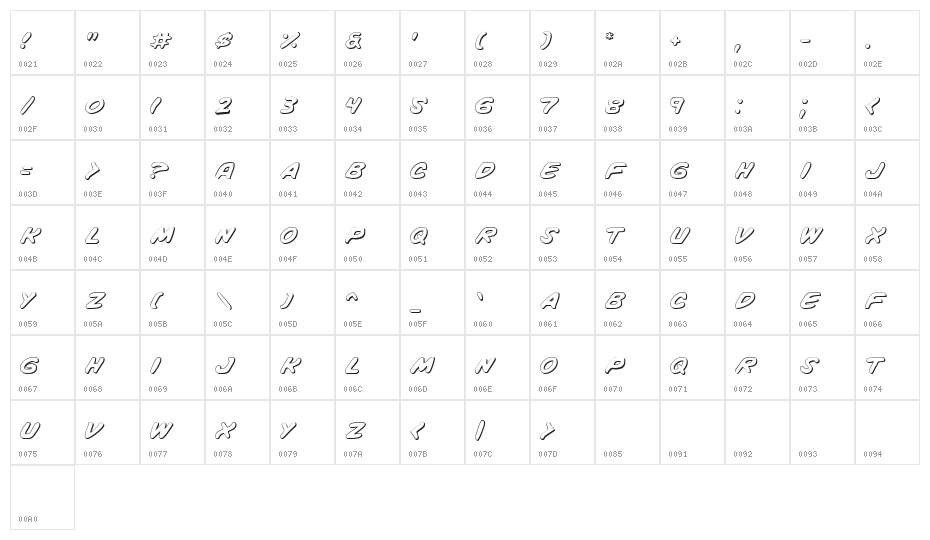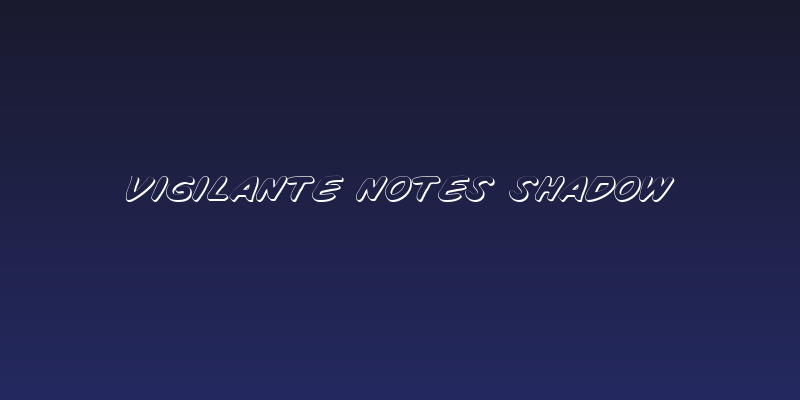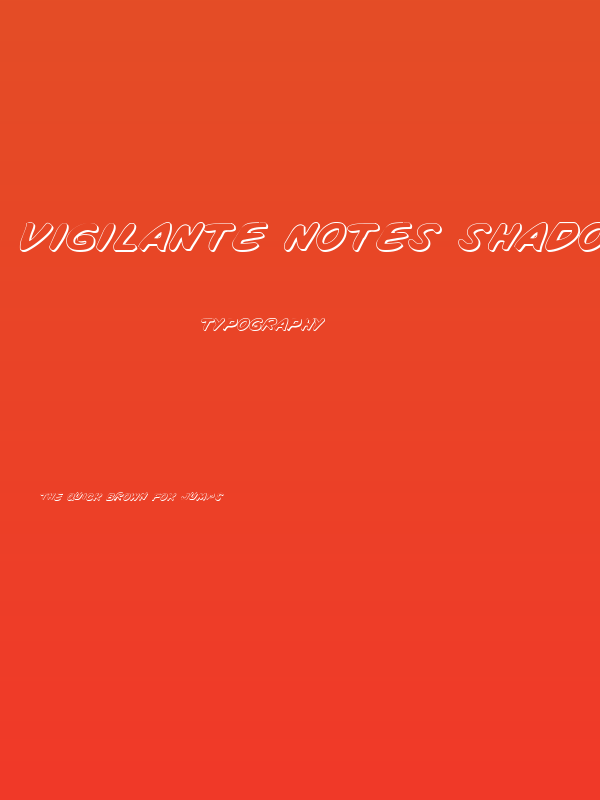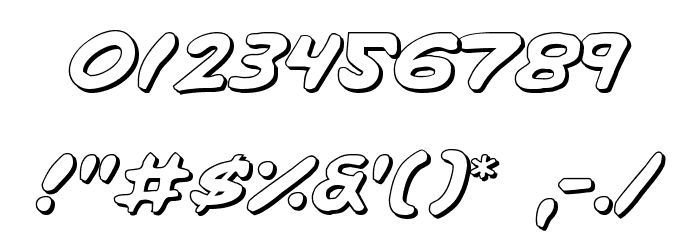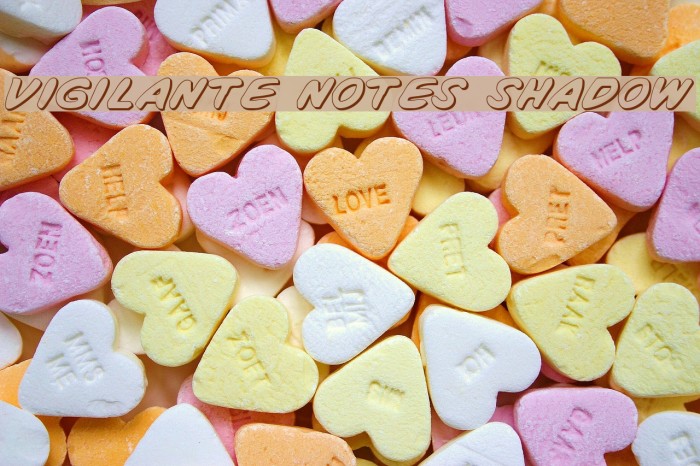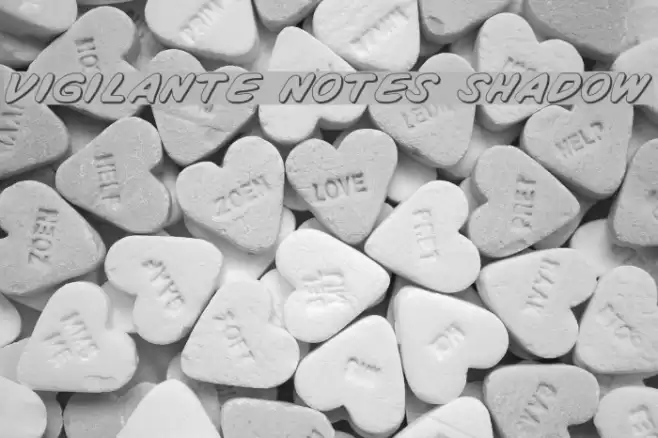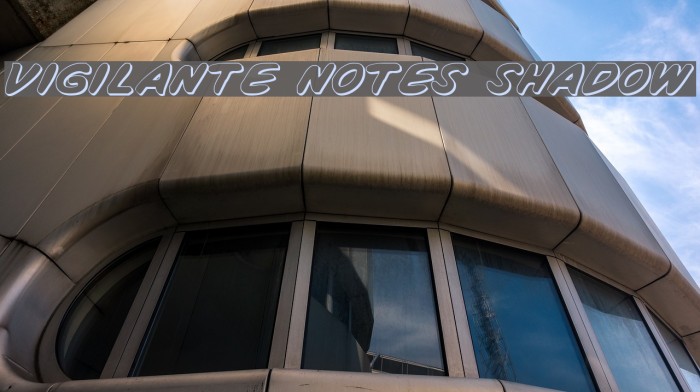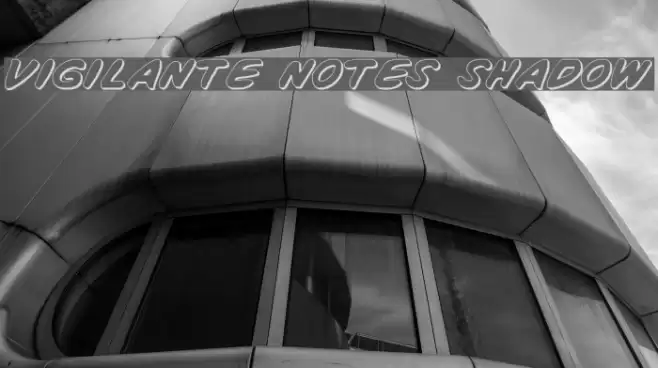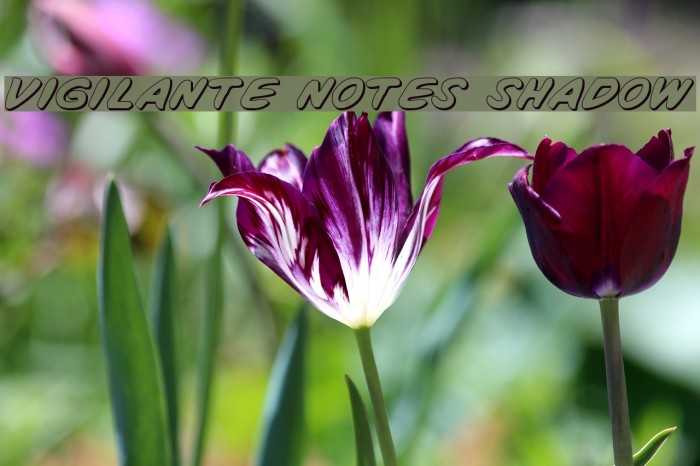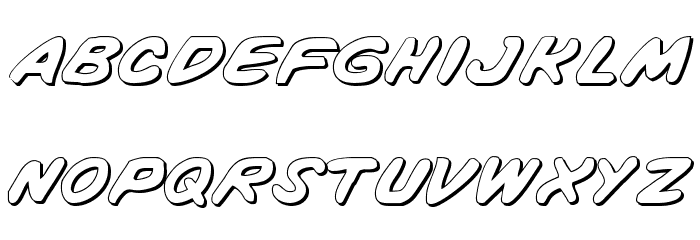
Vigilante Notes Shadow Font
✎ Comic
| समग्र शैली | Playful, Dynamic |
| उपयोग का मामला | Headlines, Logos, Posters |
| सुझाए गए प्रोजेक्ट | Ideal for comic books, children's books, posters, and playful branding projects. |